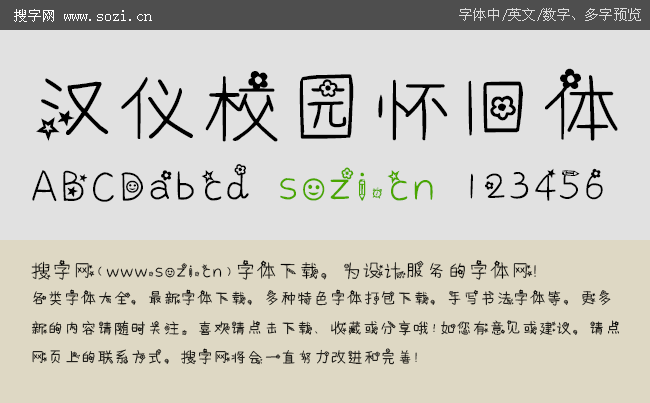
漢儀校園懷舊體
搜字網(wǎng)給大家提供一款漢儀校園懷舊體手機(jī)中文字體下載。這款手機(jī)字體是仿照兒童手寫風(fēng)格的卡通手寫字體,像小時(shí)候的手抄字一樣,一筆一劃,有些童真,有些工整,字體間還插入了有趣卡通圖案,特別適合喜歡手機(jī)字體個(gè)性一些的朋友在手機(jī)上安裝使用。